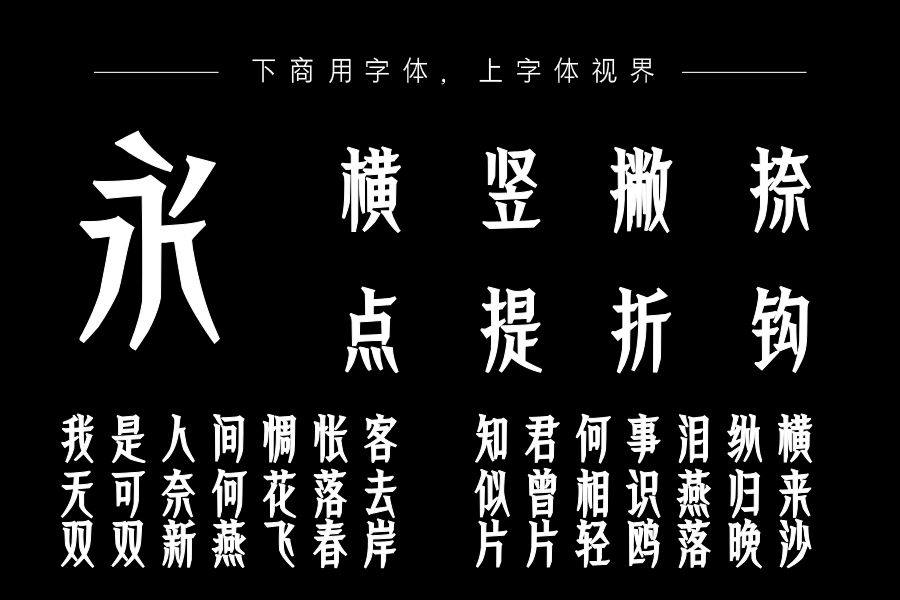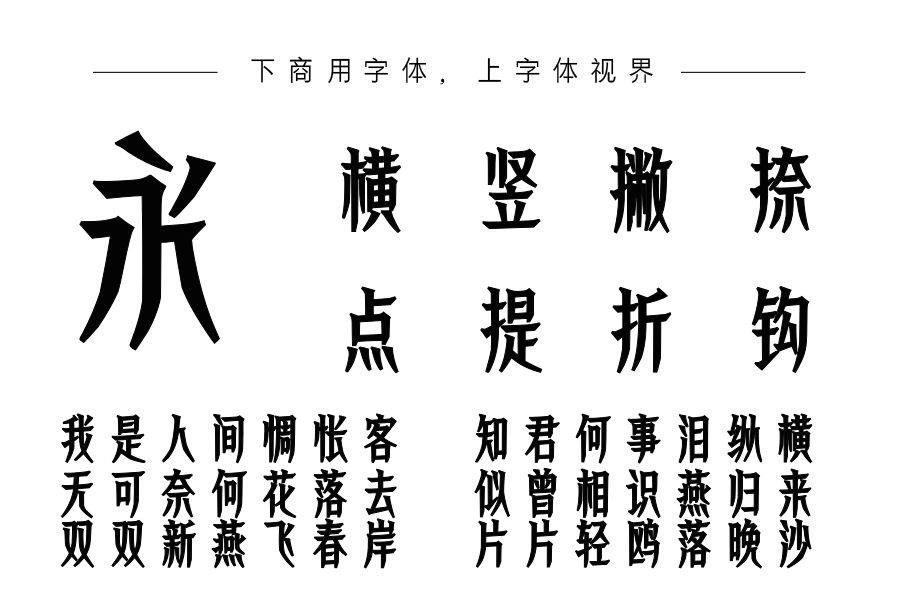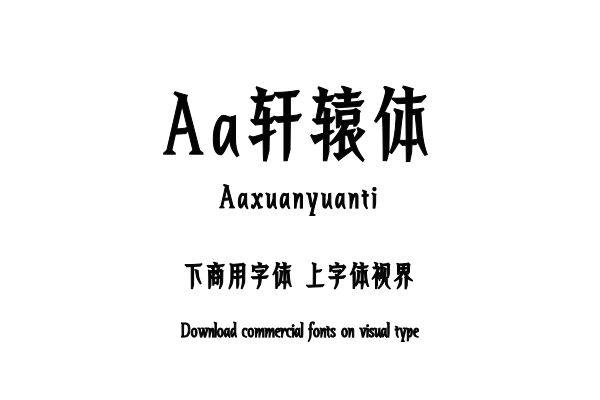
从中国古代神话传说中汲取灵感,将传统篆书书法艺术融入现代字形中,这款字体字⾯修⻓,重⼼较⾼,中宫收紧,营造庄重感,笔画多以纵向延伸,并带有⼑刻⼒量感,风格复古,......购买须知:“下载服务费”与“字体VIP”所获得字体 仅用于个人非商用, 商用请联系付费授权。本字体为电脑用字,手机没有root权限不支持直接手机换字(手机如何root,请自行百度搜索教程)。购买前请先 了解清楚后再付款 ,字体为虚拟产品无法回收 一旦购买不支持退款。